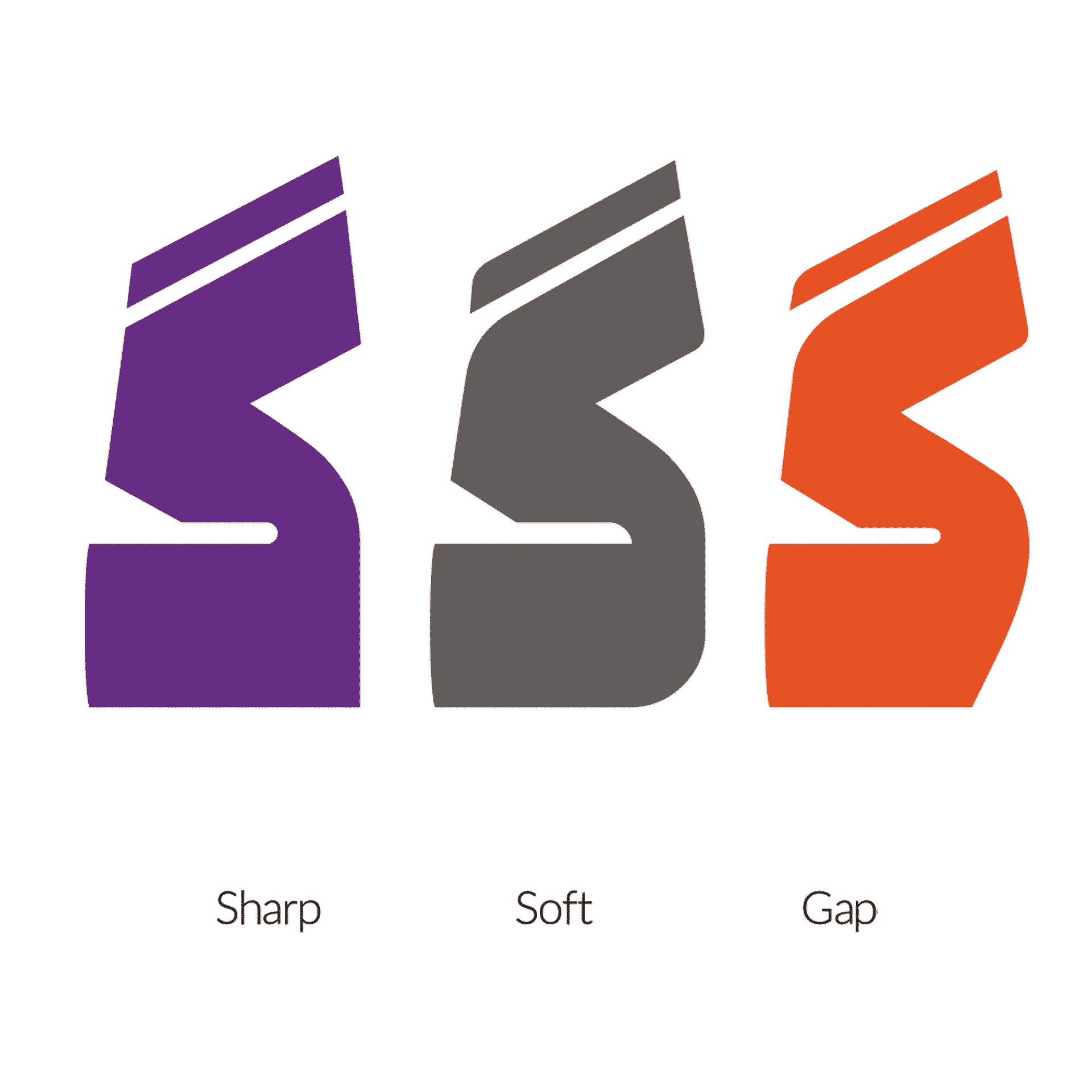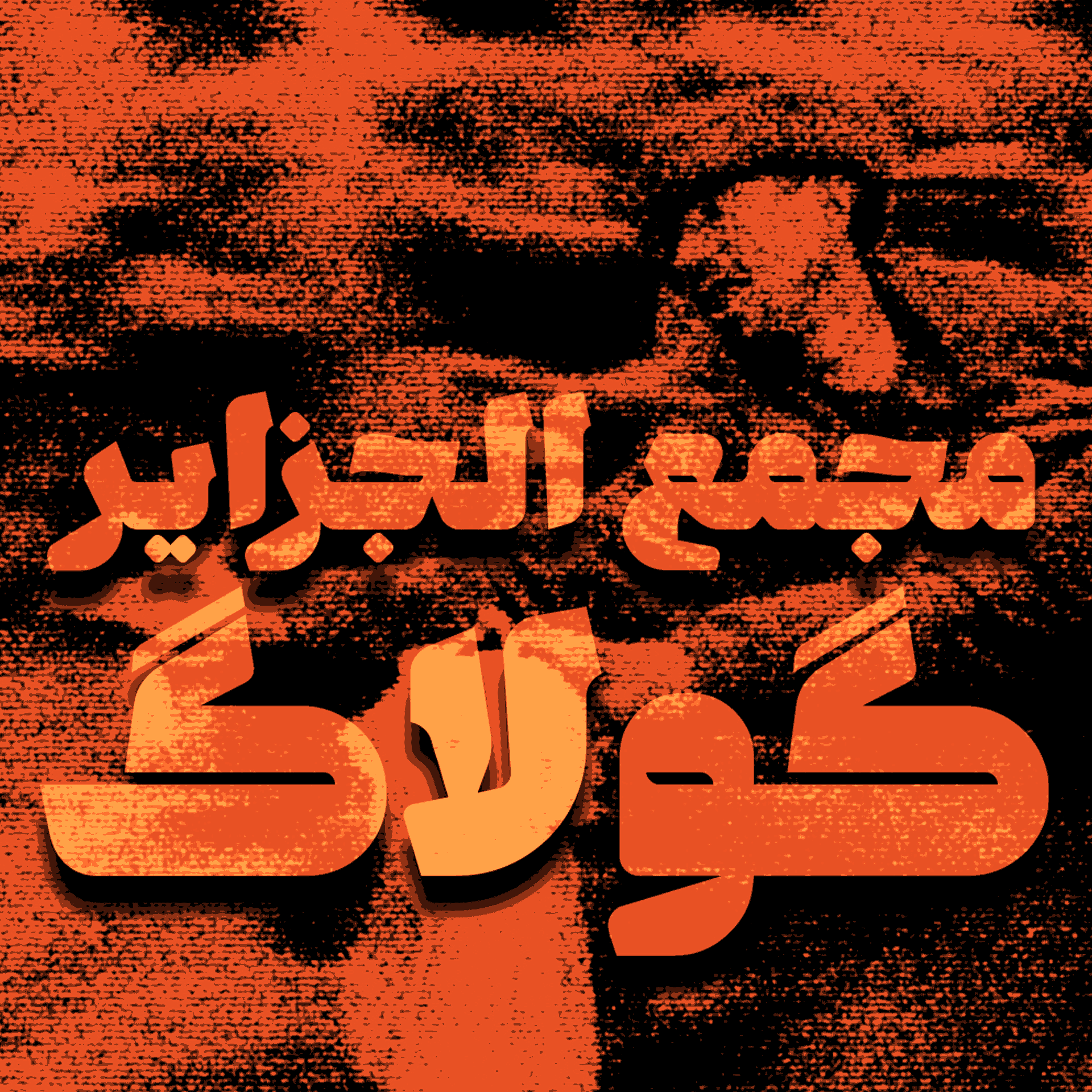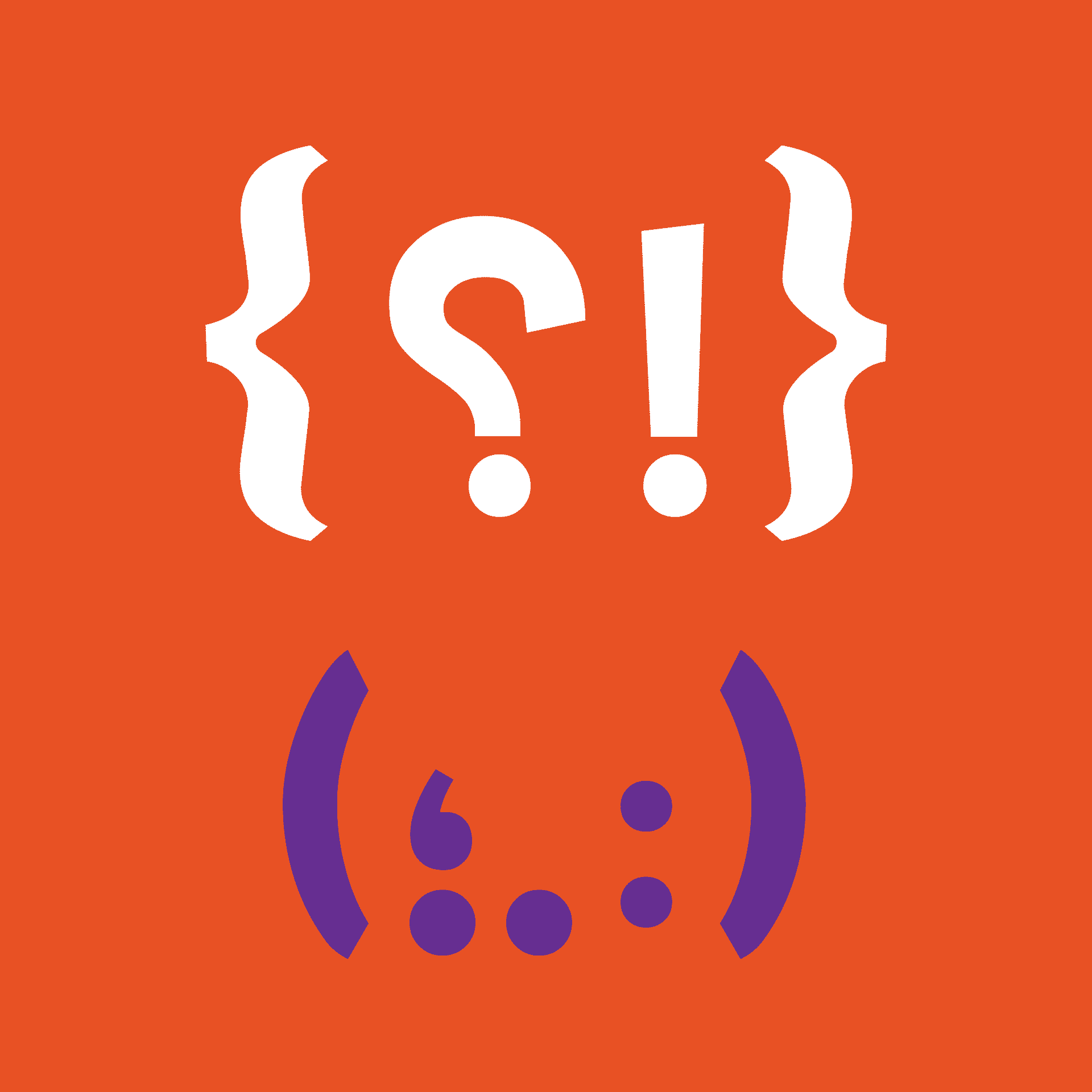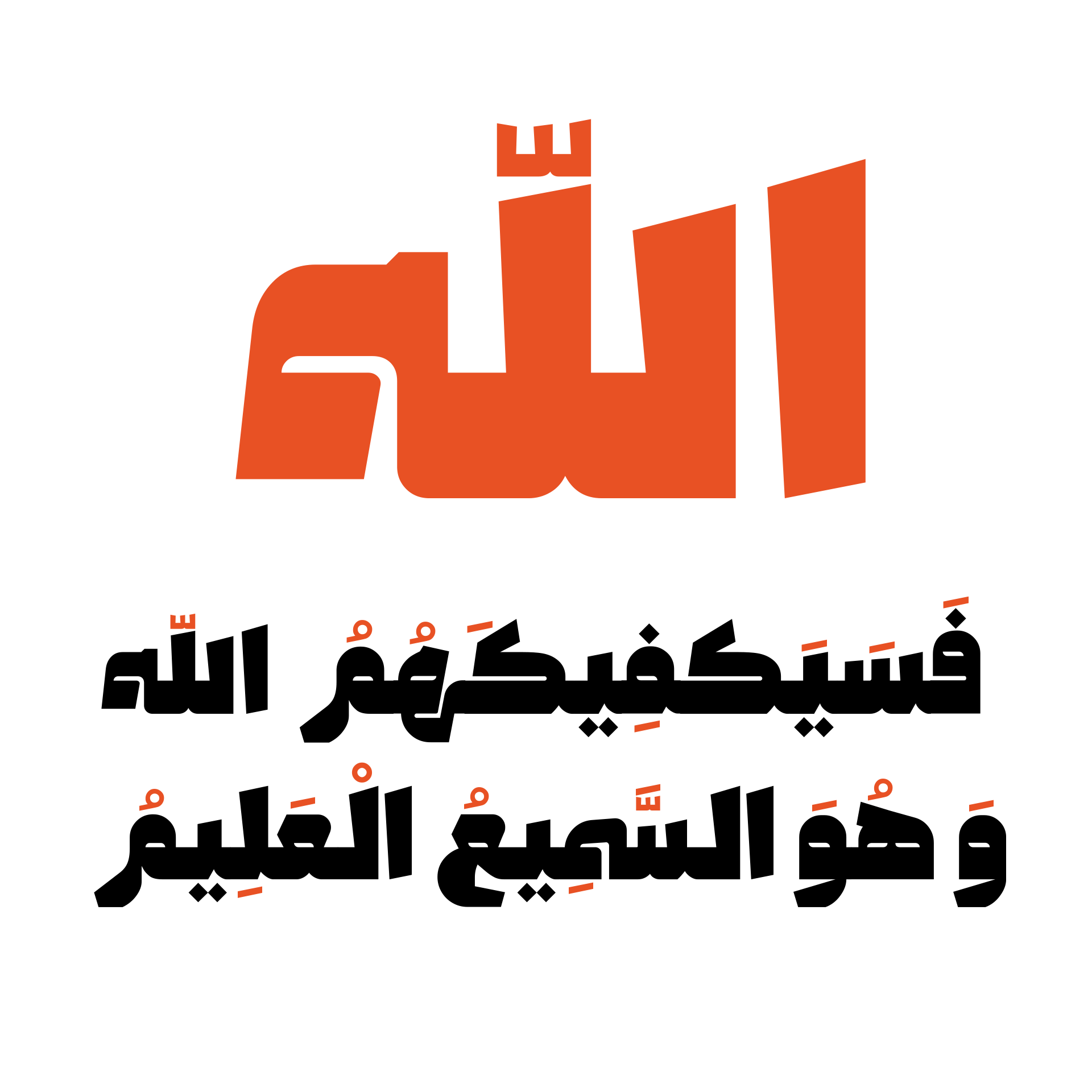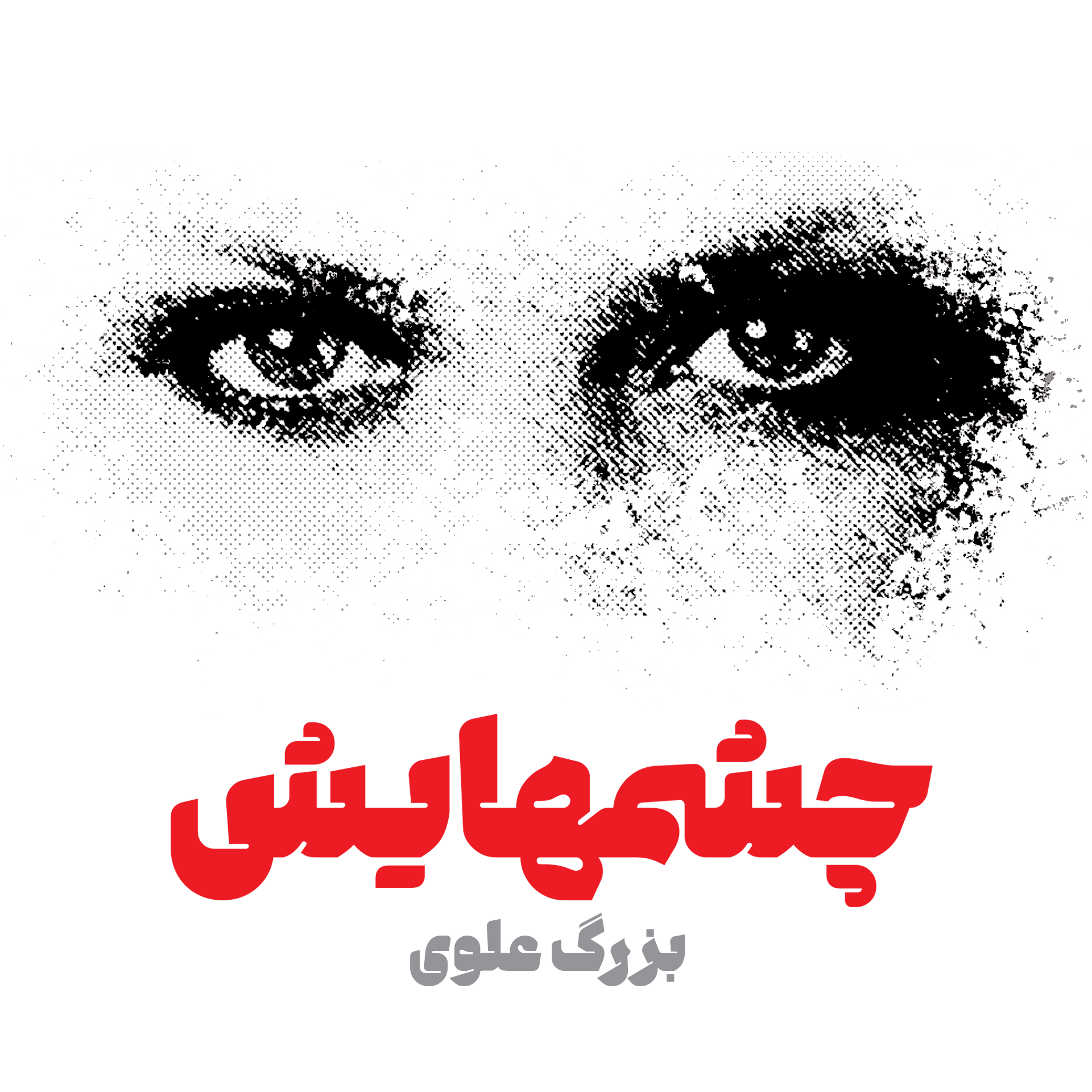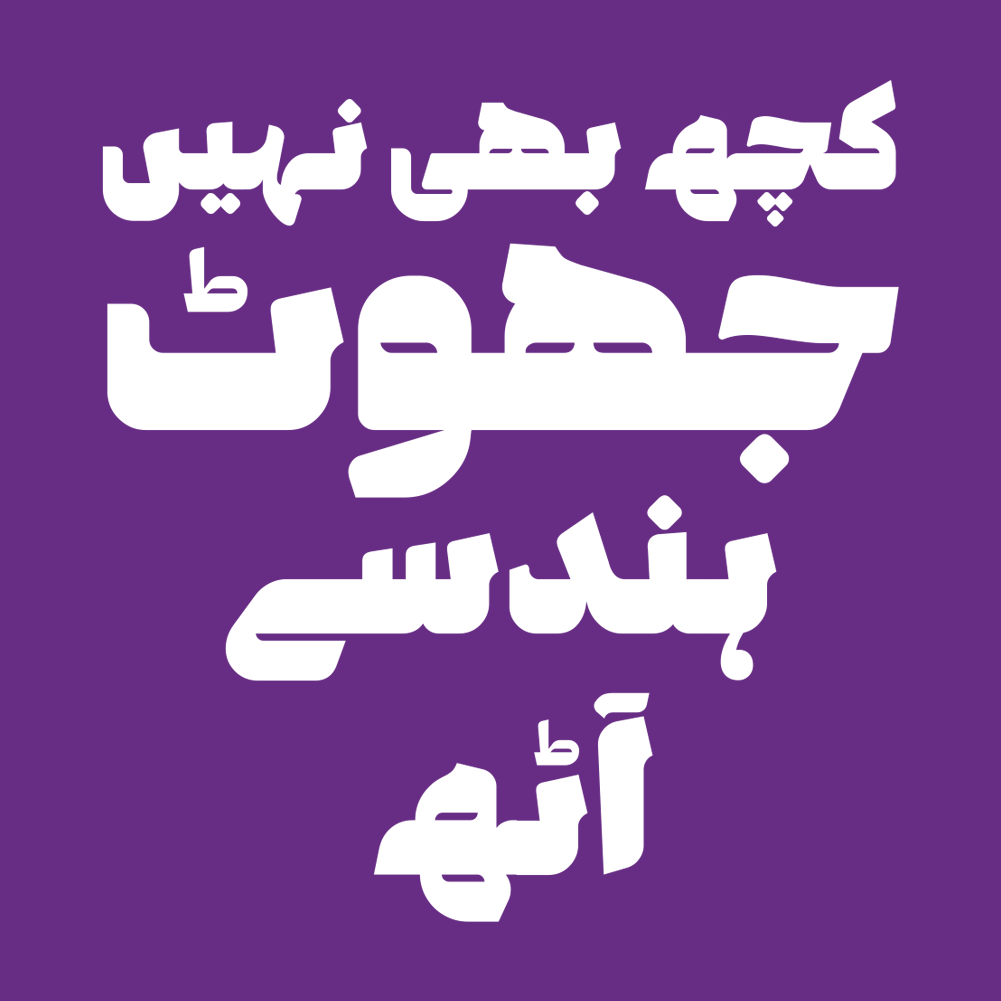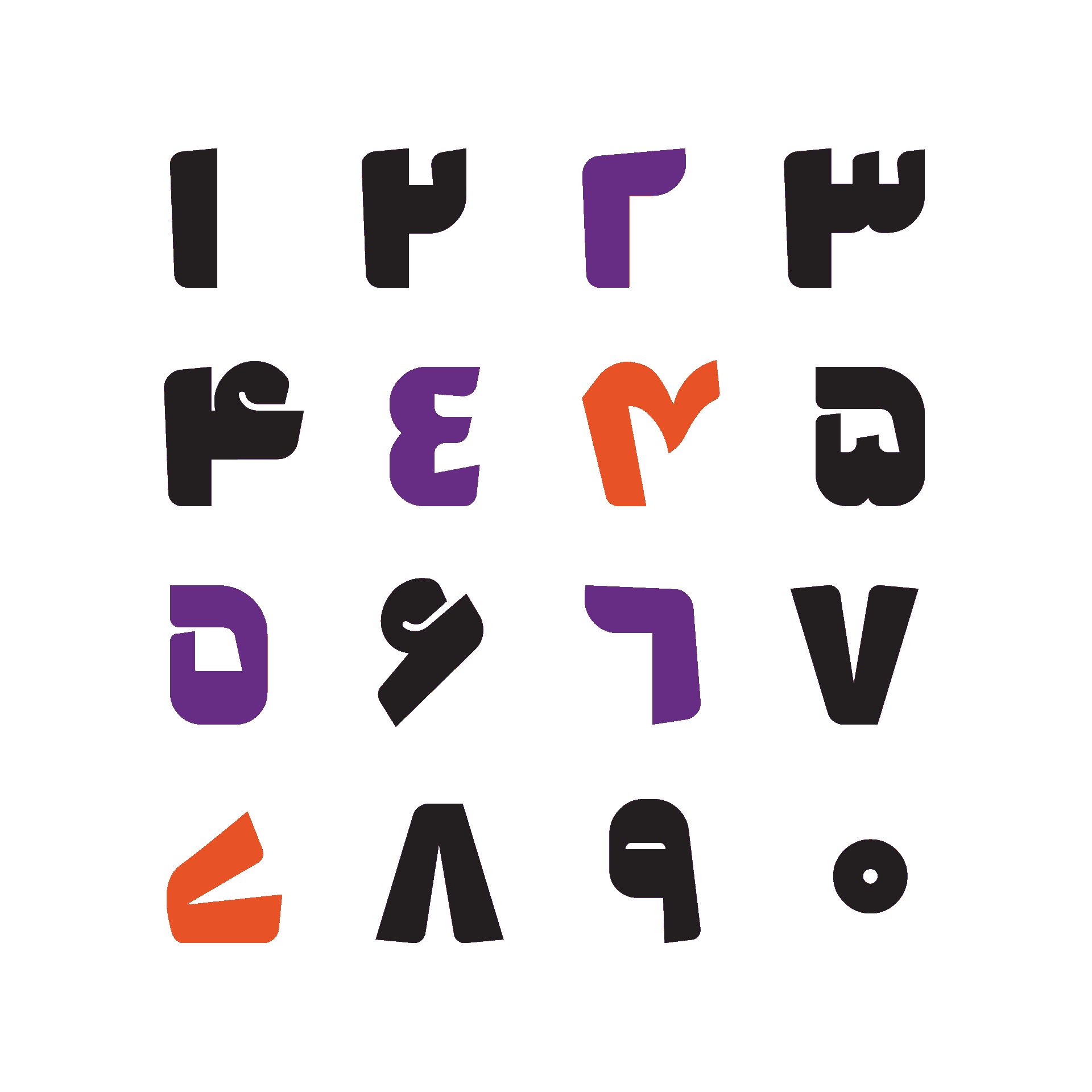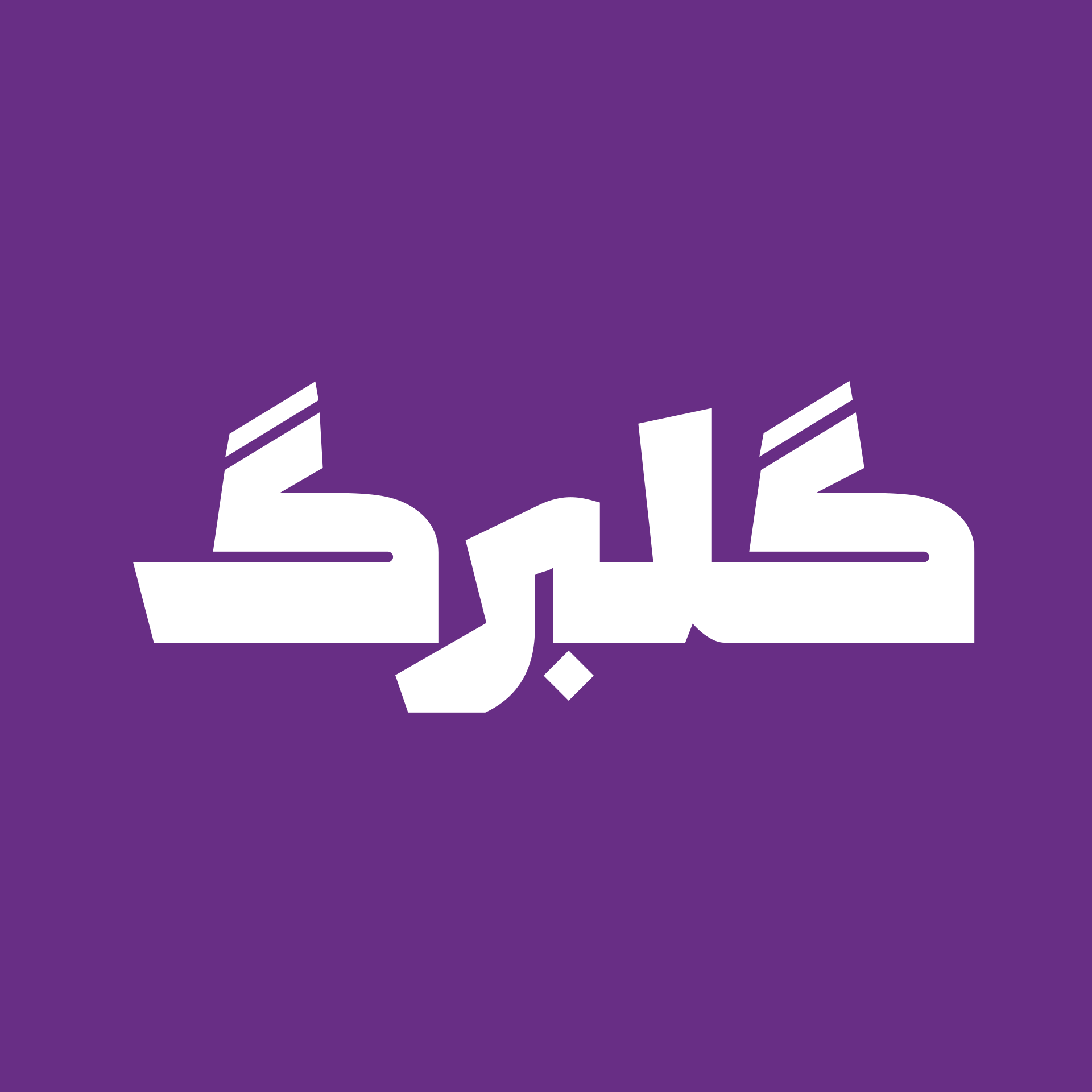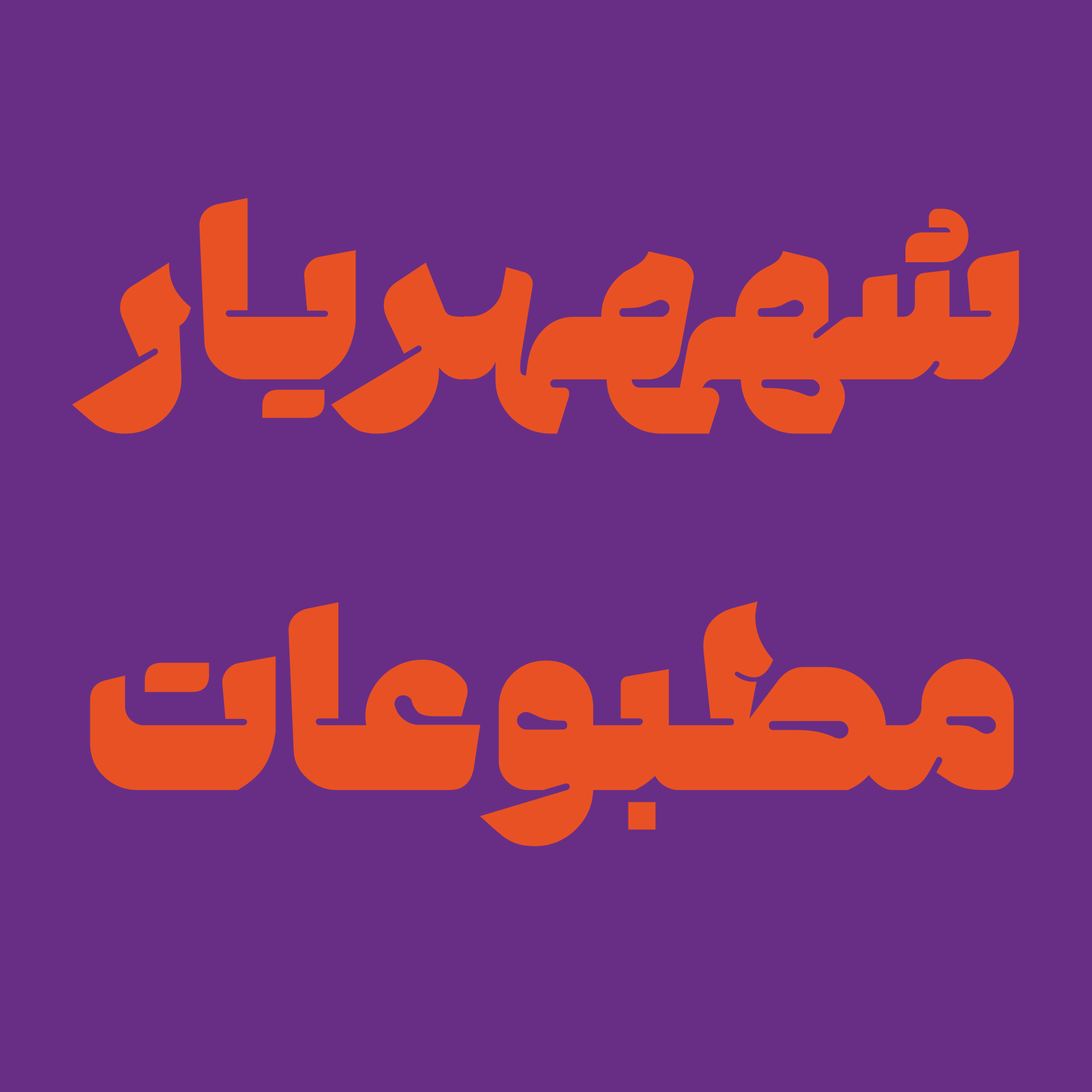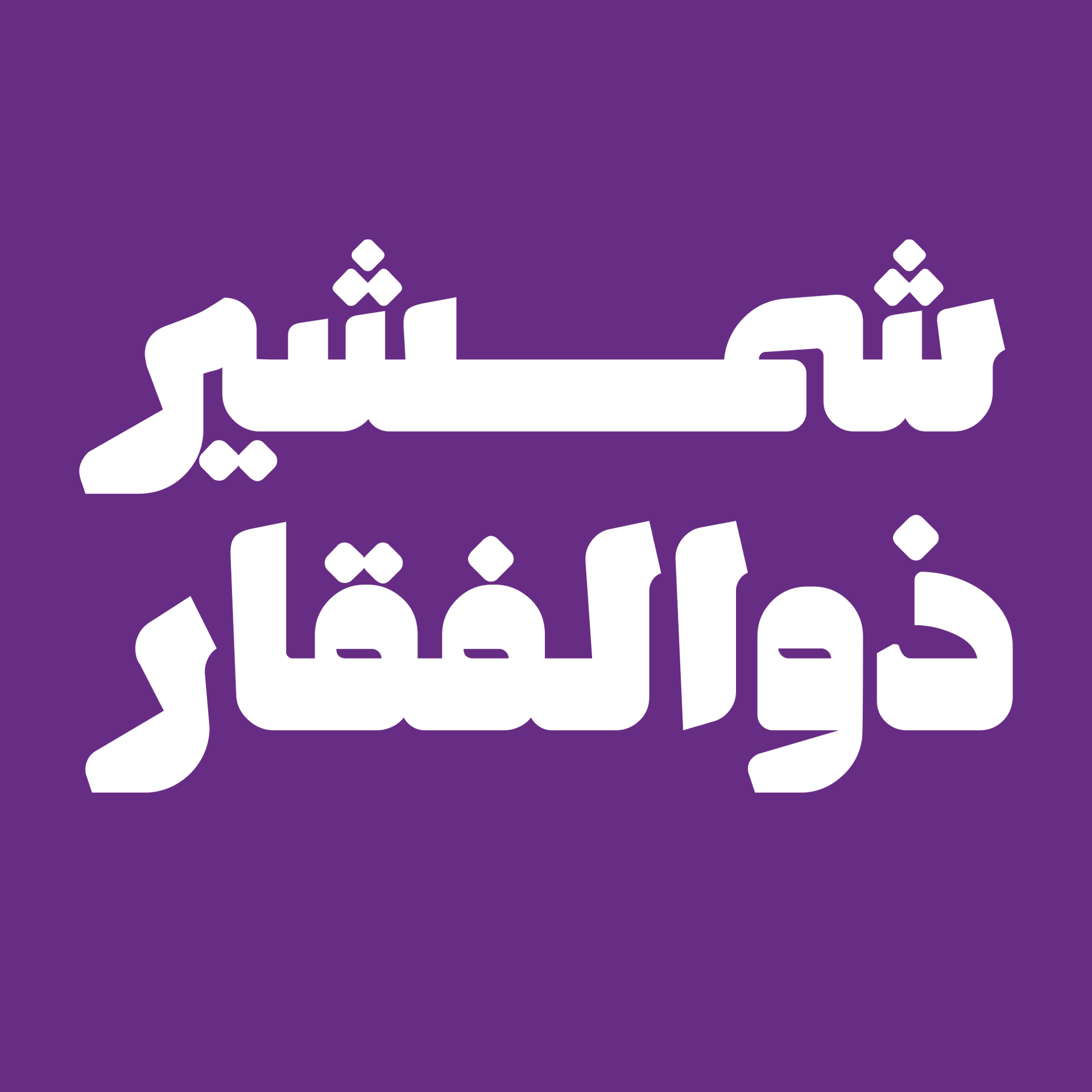
فونت وزین سافت با زوایای گردتر و تیزی های کمتر که حروف آن ضخیم تر از فونت های معمولی هستند. این فونت برای برجسته کردن یک واژه در تبلیغات یا تیتر یک مطلب استفاده می شود. وزین سافت با زوایای گرد برای استفاده در عناوین، سرفصل ها و سایر متن هایی که باید به چشم بیایند، مناسب هستند.
فونتهای سنگین با فضاهای منفی کم، نوعی فونت قدرتمند و تأثیرگذار هستند که فونت وزین از این گونه است که میتوانند برای ایجاد احساسات مختلفی استفاده شوند.
هنگام انتخاب فونت سنگین با فضاهای منفی کم، مهم است که سبک و برنامه استفاده را در نظر بگیرید.
این فونتها اغلب برای عناوین و متنهای برجسته استفاده میشوند و میتوانند برای دیده شدن یک پیام کوتاه یک یا چند کلمه ای مورد استفاده قرار گیرند.